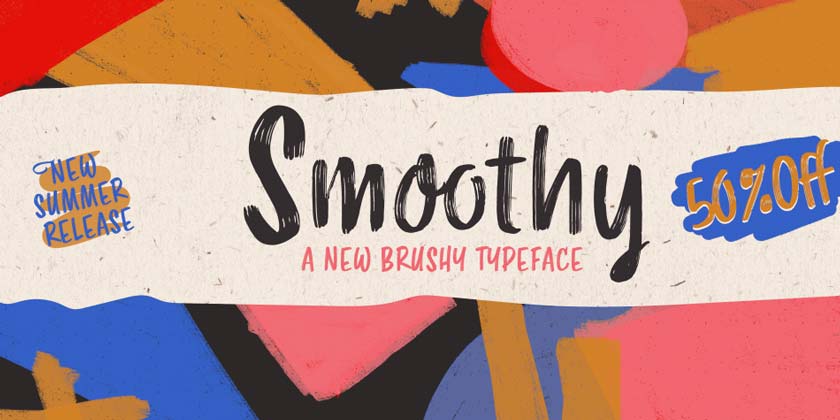
Smoothy Rsz یک فونت طراحی بسیار زیبا و جذاب پرمیوم میباشد که توسط Resistenza.es طراحی شده است و با قیمت 39 دلار (19.50 با تخفیف) بفروش میرسد. این قلم جذاب و حرفهای مناسب انواع طرح ها و پروژه های گرافیکی است که میتوان از آن در پوسترها، عناوین، تایتل ها و … استفاده کرد. هم اکنون نسخه نهایی این فونت آماده دریافت رایگان از نال اکس میباشد.
- طراحی دقیق و کاملا حرفه ای
- نمایش بی نقص تمامی حروف و اعداد بدون مشکل
- مناسب برای انواع طرح های گرافیکی
- مناسب برای ساخت و طراحی فونت، پوستر، لیبل و …
Designed by Giuseppe Salerno and Paco González, Smoothy Rsz is a brush script font family. This typeface has two styles and was published by Resistenza.es.